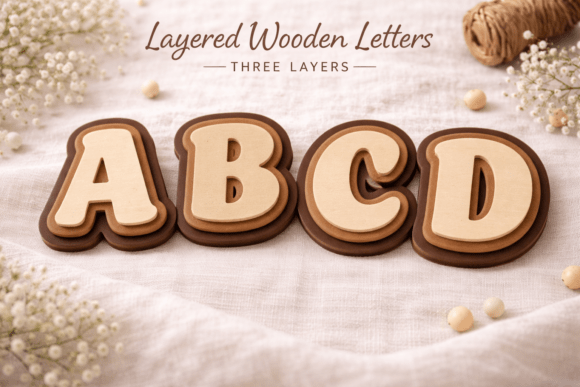
Layered Alphabet Letters SVG
Việc tìm kiếm các thành phần thiết kế phù hợp có thể là một thách thức, nhưng Layered Alphabet Letters SVG cung cấp một bộ sưu tập đặc biệt giúp nâng tầm công việc của bạn ngay lập tức.
Được chế tác với độ chính xác cao, Layered Alphabet Letters SVG cung cấp các vector sạch, kiểu chữ mượt mà và giấy phép thương mại để bạn yên tâm.